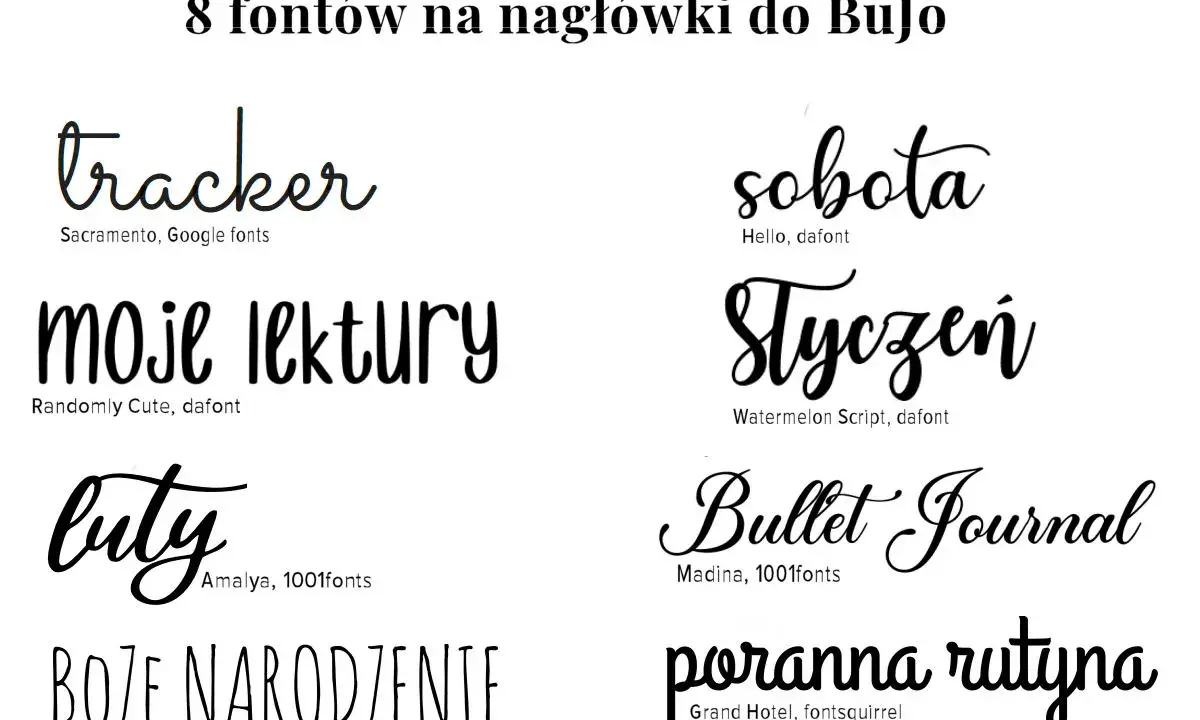
Kaligraficzne pismo przyciąga uwagę, bo łączy dekoracyjność z ruchem ręki i od razu buduje nastrój elegancji, rzemiosła albo premium. W projektach graficznych działa jednak najlepiej wtedy, gdy ma konkretną rolę: podbija emocje, ale nie konkuruje z treścią. Poniżej pokazuję, czym różni się odręczna pisanka od typografii i letteringów, gdzie sprawdza się najlepiej oraz jak dobrać krój, żeby nie stracić czytelności.
Najważniejsze rzeczy, które warto wiedzieć od razu
- Ozdobne pismo najlepiej działa jako akcent, nagłówek, logo albo detal, a nie jako baza długiego tekstu.
- W projektach warto odróżniać kaligrafię, lettering i typografię, bo każde z nich ma inne zasady i inne zastosowanie.
- Największym zagrożeniem jest spadek czytelności, zwłaszcza przy małym rozmiarze, złym odstępie i braku polskich znaków.
- Przy doborze kroju liczą się kontrast kresek, kerning, interlinia i liczba ozdobników.
- Najbezpieczniej łączyć jedną dekoracyjną pisankę z prostym fontem pomocniczym.
- W identyfikacji marki lepiej wygrywa spójność i umiarkowanie niż efekt „na siłę artystyczny”.
Czym jest ozdobne pismo i kiedy naprawdę działa
Ozdobne pismo to taki sposób zapisu liter, w którym ważna jest nie tylko treść, ale też rytm kreski, płynność ruchu i charakter znaków. W praktyce chodzi o styl oparty na ręcznym geście albo jego cyfrowej interpretacji: smukłych połączeniach, wyraźnym kontraście grubości, zawijasach i inicjałach. Najlepiej działa tam, gdzie tekst ma wywołać emocję, a nie tylko przekazać informację.
Z mojego punktu widzenia to właśnie tu wiele osób popełnia pierwszy błąd: traktuje dekoracyjny krój jak uniwersalne rozwiązanie. Tymczasem taki styl ma sens w zaproszeniach, logo, opakowaniach, podpisach, krótkich hasłach i wyróżnionych fragmentach. Gdy zaczynasz nim składać długi akapit, efekt zwykle się rozsypuje. Czytelnik zamiast „ładnie” widzi po prostu „męcząco”.
W typografii nie chodzi więc o samą ozdobność, tylko o kontrolę wrażenia. Jeśli litera ma przyciągać wzrok, musi też dać się odczytać bez wysiłku. To ważna granica, bo od niej zależy, czy projekt wygląda świadomie, czy przypadkowo. Ten podział najlepiej widać, gdy zestawi się kaligrafię z letteringiem i klasycznym składem.
Jak odróżnić kaligrafię, lettering i typografię
Te trzy pojęcia bywają mieszane, a dla projektanta to kosztowny skrót myślowy. Każde z nich działa inaczej, ma inną logikę i inaczej wpływa na odbiór projektu. Najprościej mówiąc: kaligrafia to zapis ruchem narzędzia, lettering to rysowanie pojedynczych liter, a typografia to układ i organizacja tekstu.
| Dziedzina | Jak powstaje | Po co się ją stosuje | Gdzie daje najlepszy efekt |
|---|---|---|---|
| Kaligrafia | Powstaje z ręcznego ruchu pióra, pędzla lub brush pena. | Buduje charakter, gest i indywidualność zapisu. | Zaproszenia, certyfikaty, podpisy, prace artystyczne. |
| Lettering | Litery są rysowane jako osobne kompozycje, często od zera. | Tworzy unikalny napis dopasowany do konkretnego projektu. | Logo, plakaty, okładki, kampanie reklamowe. |
| Typografia | Opiera się na wyborze kroju, składu, hierarchii i odstępów. | Porządkuje treść i zwiększa czytelność komunikatu. | Strony internetowe, artykuły, katalogi, identyfikacja marki. |
Ta różnica jest praktyczna, nie akademicka. Jeśli pracujesz nad kampanią reklamową, typografia pomoże ci zbudować hierarchię informacji, a kaligraficzny akcent może dodać emocji. Jeśli projektujesz logo, lettering daje największą swobodę. Jeśli przygotowujesz stronę lub ofertę, typografia musi utrzymać czytelność, a ozdobny styl powinien zostać ograniczony do nagłówka albo detalu.
Właśnie dlatego nie warto pytać, „co jest ładniejsze”. Lepiej pytać, co ma zrobić ten znak w projekcie. Od tego zależy, czy wybierzesz pismo ręczne, autorski napis, czy zwykły krój z eleganckim szeryfem. I to prowadzi wprost do najważniejszej kwestii: gdzie taki styl działa najlepiej, a gdzie zwyczajnie przeszkadza.
Gdzie dekoracyjna pisanka daje najlepszy efekt
Najbardziej naturalne zastosowania tego stylu to projekty, w których liczy się klimat: branding premium, śluby, beauty, handmade, gastronomia, lifestyle i krótkie hasła reklamowe. W takich miejscach ozdobne litery nie tylko zdobią, ale też sygnalizują jakość, intymność albo rzemieślniczy charakter. Dobrze zrobione potrafią podnieść wartość postrzeganą marki bez zmiany samej oferty.
- Logo i znak marki - szczególnie wtedy, gdy chcesz podkreślić osobisty, autorski charakter.
- Zaproszenia i wydarzenia - tu odręczność buduje wrażenie wyjątkowości i uroczystości.
- Opakowania - działa świetnie na kosmetykach, produktach rzemieślniczych i prezentowych.
- Social media - jako krótki akcent na planszy, okładce karuzeli albo wyróżnionym cytacie.
- Menu i komunikacja lokalu - zwłaszcza tam, gdzie marka sprzedaje atmosferę równie mocno jak produkt.
Jest też druga strona medalu. Ten sam styl łatwo męczy w treściach informacyjnych, ofertach B2B, długich opisach produktów i interfejsach, gdzie użytkownik chce dotrzeć do informacji, a nie podziwiać krój. Na ekranie telefonu problem zwykle rośnie, bo cienkie zakończenia i ozdobniki znikają szybciej niż na monitorze. Jeśli więc projekt ma być responsywny, sprawdzam dekoracyjny krój na małym ekranie jako pierwszy, nie ostatni krok.
W praktyce najlepiej działa zasada kontrastu: im bardziej ozdobne pismo, tym prostsze powinno być wszystko wokół niego. I właśnie dlatego dobór kroju oraz proporcji ma tu większe znaczenie niż sama „ładność” liter.
Jak dobrać krój, żeby zachować czytelność
W typografii ozdobnej największą wartość ma nie efekt „wow”, tylko to, czy projekt nadal da się odczytać po dwóch sekundach. Ja zwykle sprawdzam cztery rzeczy: rozmiar, odstępy, kontrast i komplet znaków. Jeśli któraś z nich się nie zgadza, nawet ładny krój zaczyna wyglądać na przypadkowy.
| Kryterium | Na co patrzeć | Dlaczego to ważne |
|---|---|---|
| Rozmiar | Przy krótkich napisach testuj większe stopnie, zwykle od 24 px wzwyż na ekranie. | Ozdobne detale i cienkie zakończenia potrzebują przestrzeni. |
| Kerning | Sprawdź odstępy między parami liter, zwłaszcza w nazwach własnych. | Zbyt luźne lub zbyt ciasne litery psują rytm i wyglądają amatorsko. |
| Interlinia | W nagłówkach i blokach tekstu zostaw więcej powietrza niż przy prostych krojach. | Zapobiega sklejaniu się ozdobnych znaków między wierszami. |
| Polskie znaki | Upewnij się, że font ma pełne wsparcie dla ą, ę, ł, ń, ó, ś, ź, ż. | Brak diakrytyków od razu obniża jakość projektu i wiarygodność marki. |
| Kontrast kresek | Porównaj cienkie i grube fragmenty liter w realnym rozmiarze publikacji. | Wysoki kontrast bywa elegancki, ale na słabych ekranach może zniknąć. |
Przy łączeniu krojów trzymam się jeszcze jednej reguły: jedna ozdobna pisanka i jeden prosty font pomocniczy to zwykle maksimum, które naprawdę działa. Możesz zestawić elegancki script z neutralnym sans serifem albo z klasycznym szeryfem, ale nie dokładaj trzeciego charakteru „dla urozmaicenia”. W praktyce to właśnie nadmiar robi największe szkody.
Jeśli projekt ma być drukowany, testuję go na wydruku próbym. Jeśli ma żyć w internecie, sprawdzam go na telefonie, w trybie ciemnym i przy mniejszym zoomie. Taka kontrola szybko ujawnia, czy krój nadal niesie komunikat, czy tylko wygląda efektownie na dużym ekranie. A kiedy sam styl już się zgadza, można przejść do budowania napisu od zera.
Jak zbudować własny efekt krok po kroku
Gdy tworzę napis inspirowany kaligrafią, najpierw myślę o strukturze, a dopiero potem o ozdobach. To ważne, bo dekoracyjność bez konstrukcji szybko kończy się chaosem. Poniższy proces sprawdza się zarówno przy pracy ręcznej, jak i cyfrowej.
- Ustal cel projektu - inny charakter ma nagłówek do luksusowej marki, a inny podpis do posta w social media.
- Wybierz narzędzie - pióro, brush pen, pędzel cyfrowy albo krój pisma stylizowany na ręczny zapis.
- Zbuduj szkic na siatce - trzymaj linię bazową, wysokość średnią i miejsca na wydłużenia liter.
- Dodaj kontrast i rytm - grubsze pociągnięcia niech mają wyraźny sens, a nie przypadkową zmienność.
- Wprowadź ozdobniki oszczędnie - zawijas, ligatura czy swash mają podkreślać literę, nie ją zasłaniać.
- Sprawdź odczyt - odsuń projekt na 2-3 metry albo zmniejsz go do miniatury; jeśli nadal działa, masz dobry kierunek.
Warto przy tym pamiętać o terminach, które często pojawiają się w pracy projektowej. Ligatura to połączenie dwóch liter w jeden znak, a swash to dekoracyjne wydłużenie albo zawijas przy literze. Oba rozwiązania potrafią dodać klasy, ale tylko wtedy, gdy są użyte z umiarem. Zbyt dużo ozdobników daje efekt „nadpisanej” kompozycji, a nie dopracowanego stylu.
Z mojego doświadczenia najlepiej działa zasada: najpierw czytelność, potem charakter, dopiero na końcu ozdoba. Jeśli odwrócisz tę kolejność, projekt często wygląda efektownie tylko na pierwszym spojrzeniu. A to w reklamie i identyfikacji marki zwykle za mało.Najczęstsze błędy, które psują projekt
Ozdobne liternictwo bywa wdzięczne, ale też bezlitosne dla drobnych błędów. Niewielka zmiana w odstępach albo za wysoki poziom dekoracyjności może całkowicie zmienić odbiór projektu. W praktyce najczęściej widzę pięć problemów.
- Zbyt długi tekst zapisany krojem dekoracyjnym, przez co projekt staje się trudny do przeczytania.
- Mieszanie kilku różnych pisanek w jednym projekcie, co zabiera spójność.
- Za mały kontrast między literami a tłem, szczególnie w social mediach i na zdjęciach produktowych.
- Ignorowanie polskich znaków, które w języku polskim są nie do pominięcia.
- Używanie cienkiego, ozdobnego fontu w rozmiarze, który dobrze wygląda tylko na makiecie, ale nie w realnym użyciu.
Jest jeszcze jeden błąd, który często widzę u osób początkujących: próba „naprawiania” słabego kroju dodatkowymi efektami. Cień, obrys, glow czy gradient nie uratują liter, jeśli sam kształt jest źle dobrany. Lepiej wybrać prostszy, ale solidniejszy font niż walczyć z krzywą konstrukcją. To samo dotyczy brandingu - jeśli styl ma budować prestiż, musi najpierw być stabilny, a dopiero potem efektowny.
Właśnie dlatego przed publikacją robię ostatni filtr: sprawdzam użycie, skalę i spójność z całą identyfikacją. Taki test zajmuje chwilę, a oszczędza godzin poprawiania projektu po wdrożeniu. I to jest ostatni krok, który naprawdę robi różnicę.
Trzy filtry, które stosuję przed publikacją projektu
Zanim uznam dekoracyjne pismo za gotowe, przepuszczam je przez trzy proste pytania. Po pierwsze: czy ten zapis wspiera komunikat, czy tylko go ozdabia? Po drugie: czy da się go odczytać bez wysiłku na ekranie telefonu i w druku? Po trzecie: czy reszta projektu jest na tyle spokojna, że ta jedna ozdobna warstwa nie musi robić wszystkiego sama?
Jeśli na wszystkie trzy odpowiedzi brzmią „tak”, projekt zwykle jest bezpieczny. Jeśli choć na jedno „nie”, wracam do kroju, odstępów albo hierarchii i upraszczam kompozycję. To właśnie umiar odróżnia dobrą pisankę od efektownej, ale nietrwałej dekoracji. W praktyce lepiej zostawić odrobinę pustej przestrzeni niż dopchnąć literę kolejnym zawijasem.
Kaligraficzny styl w typografii nie musi być krzykliwy, żeby działał. Najmocniej pracuje wtedy, gdy wygląda naturalnie, ma sens w kontekście marki i nie walczy z treścią. Jeśli trzymasz się tej zasady, dostajesz narzędzie, które potrafi dodać projektowi klasy, lekkości albo charakteru bez utraty czytelności.